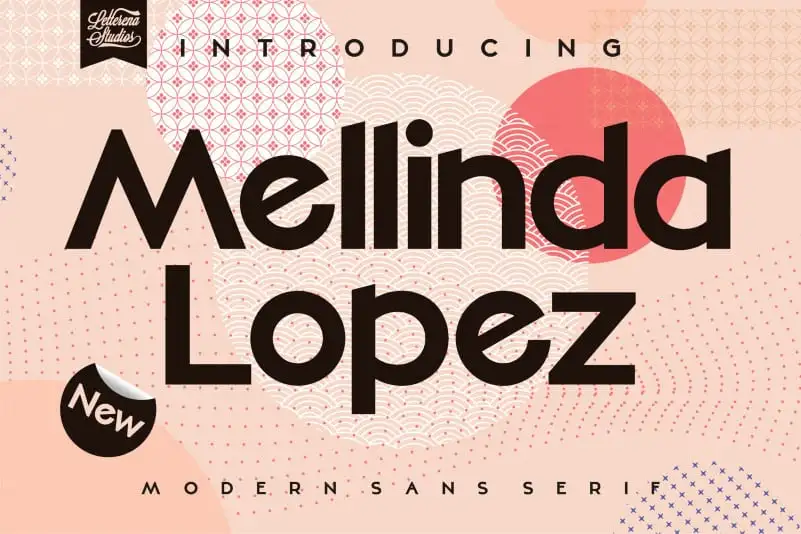
Mellinda Lopez Sans Serif Font – Fonte Grátis
Mellinda Lopez Sans Serif Font
A Mellinda Lopez Sans Serif é uma fonte moderna e elegante que se destaca no mundo dos tipos de letras sem serif. Esta fonte perfeita para uma ampla variedade de projetos, como logotipos, identidades de marca, embalagens de produtos, cartazes, sacolas de compras, camisetas personalizadas, capas de livros, convites de aniversário, selos, fotografia e até mesmo marcas especiais. Com seu design minimalista e moderno, a Mellinda Lopez Sans Serif é uma ótima opção para qualquer projeto que busque um toque bonito e sofisticado. É perfeita tanto para projetos de escritório quanto para criações mais imprevisíveis, garantindo sempre um resultado profissional e inovador. Seja qual seja o seu objetivo gráfico, esta fonte lhe ajudará a destacar-se.